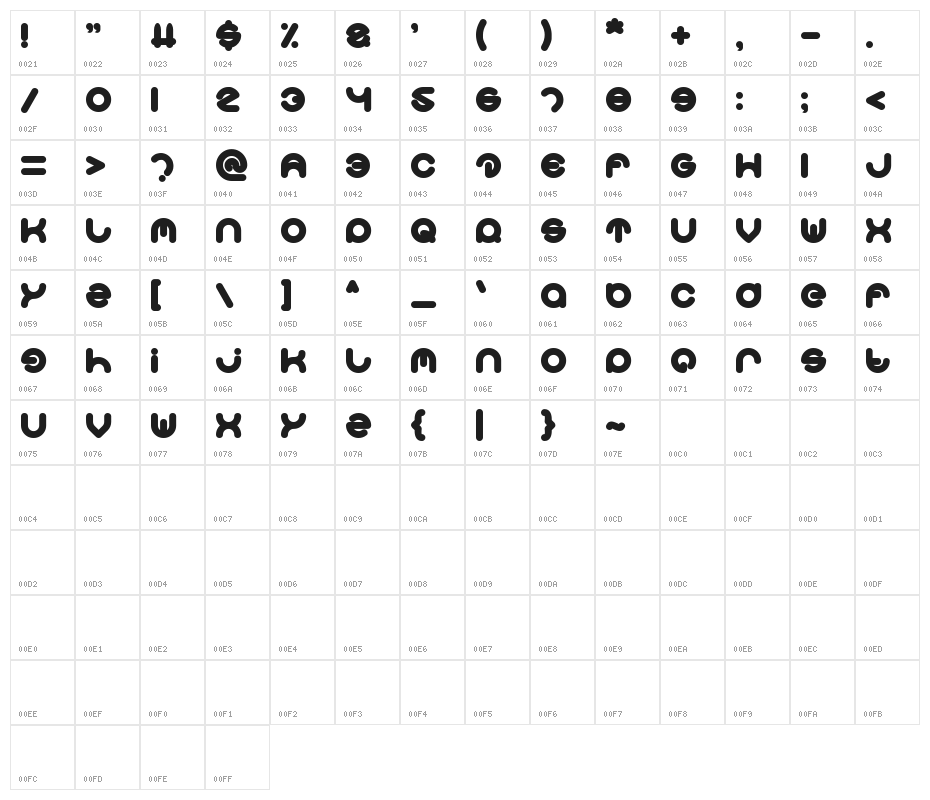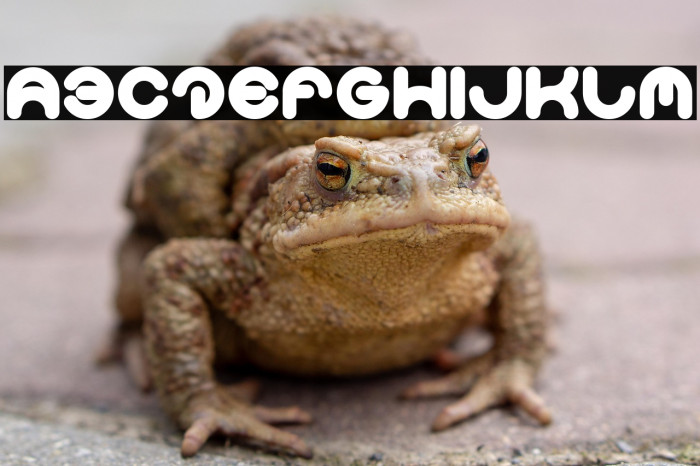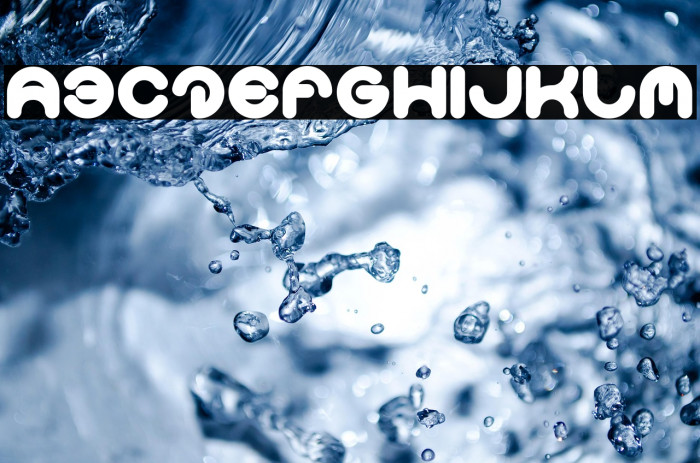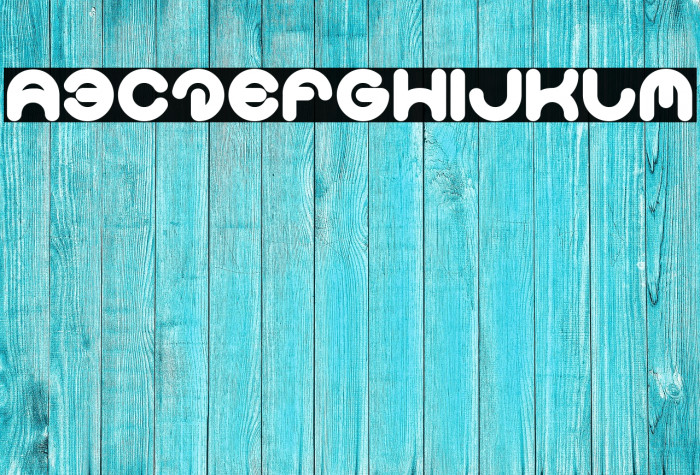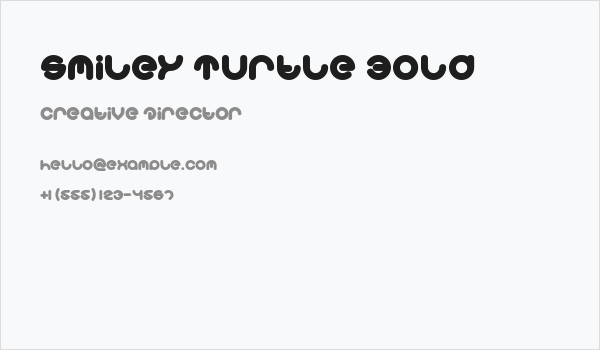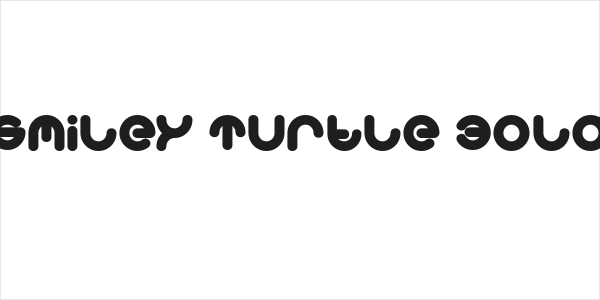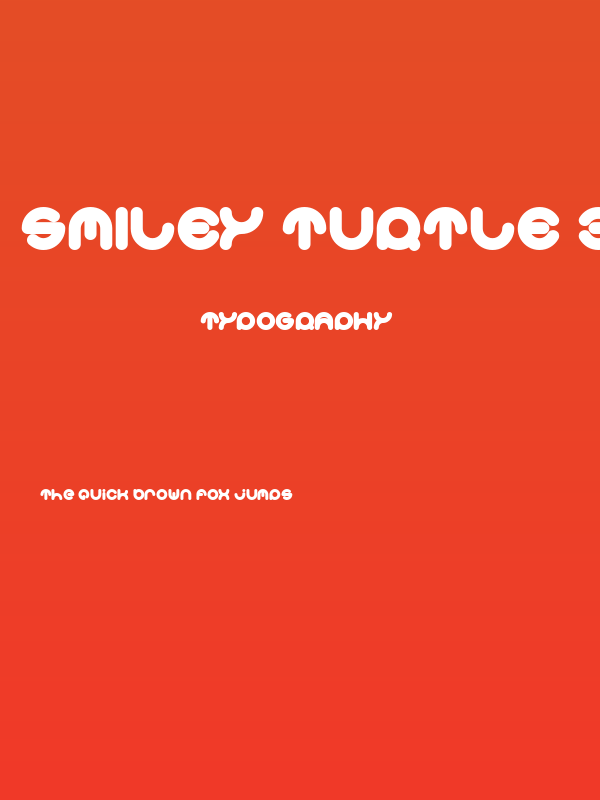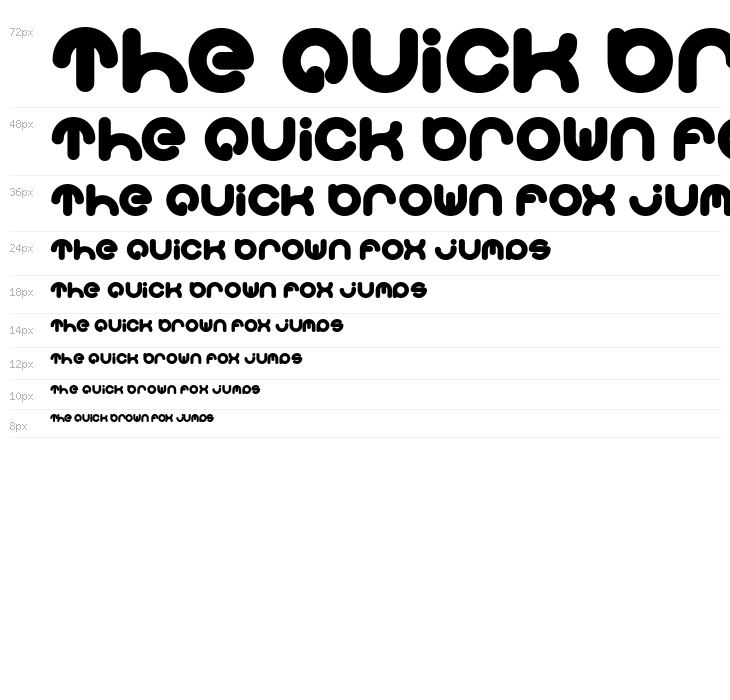
Smiley Turtle Bold Font
| Nome | Smiley Turtle Bold |
| Stile generale | Modern, Whimsical |
| Progetti proposti | Ideal for children's books, playful branding, party invitations, and creative posters. |